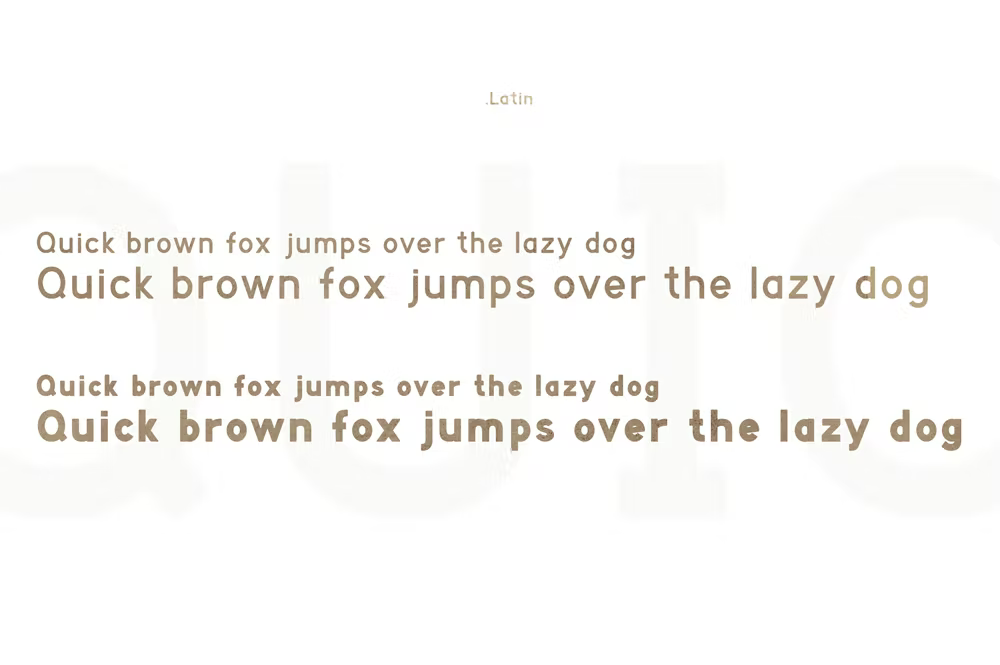
CornerOne Font
CornerOne Font Police simple et ronde, parfaite pour les publicités vintage, absolument toutes les introductions, présentations. Clair, concis, le meilleur – CornerOne.
Incluez toutes les lettres, chiffres et certains glyphes. Disponible en 2 styles : gras et régulier, et en 2 alphabets : latin et cyrillique.